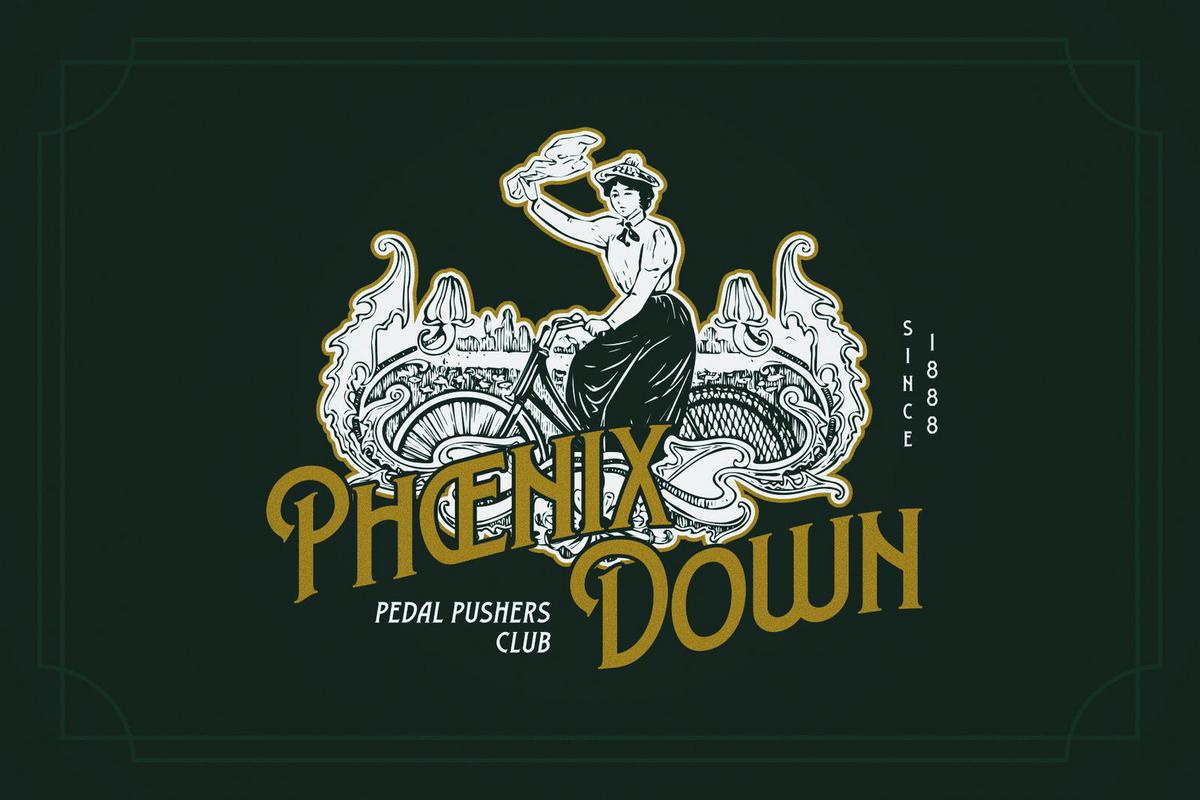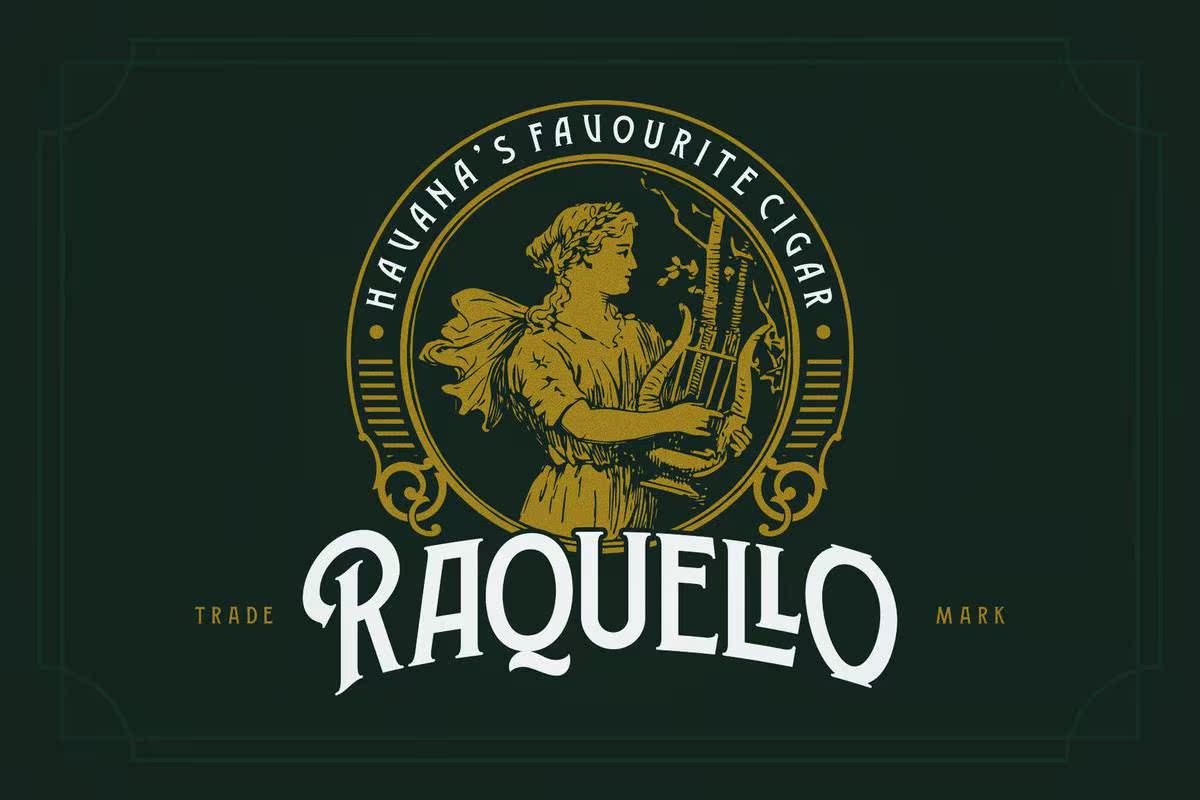
介绍新字体;此外,aclassicart deco是一种受包装标签和广告中使用的LD排版/文字启发的系列。此字体加载了300多个字形,包装中没有任何其他字符,可提供多种文字组合,无需再使用。如果您喜欢经典的DART-Decoish排版,请确保将此字体添加到您的设计工具箱中。简介新字体;此外,aclassicart deco是一种受包装标签和广告中使用的LD排版/文字启发的系列。此字体加载了300多个字形,包装中没有许多可选字符,可提供多种文字组合,停止播放。如果您喜欢经典的DART-Decoish排版,请确保将此字体添加到您的设计工具箱中。